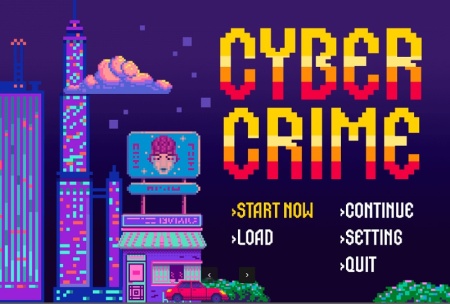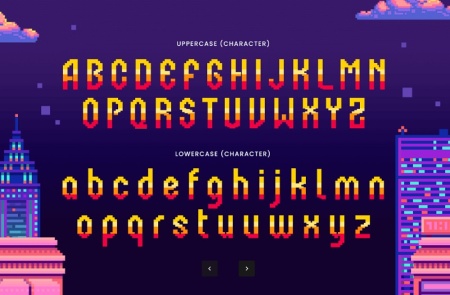
دانلود فونت انگلیسی پیکسلی Bitmap Pixel Font
دانلود فونت انگلیسی پیکسلی Bitmap Pixel Font از جی اف ایکس دانلود. فونت انگلیسی پیکسلی مناسب برای طراحی های گرافیکی، تبلیغاتی، گرافیک‌های کامپیوتری قدیمی و بازی‌های ویدیویی دهه 80 و 90 و طراحی پوسترها و بنرهای تبلیغاتی با تم رترو میلادی است.
فونت انگلیسی پیکسلی Bitmap Pixel Font
فونت پیکسلی انگلیسی Bitmap Pixel Font
✅ نام فونت انگلیسی: Bitmap - Pixel Font
✅ حروف بزرگ و کوچک/ علامت گذاری، عدد و نماد